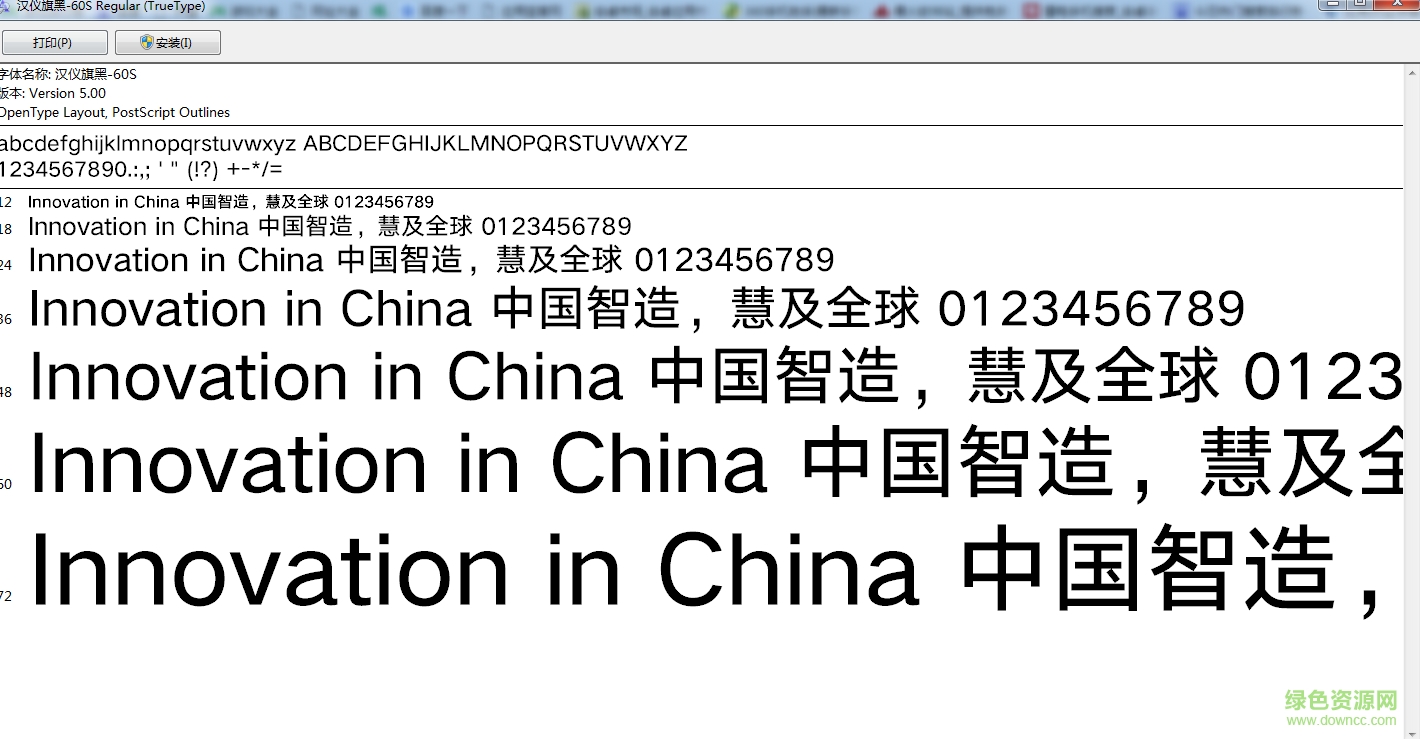
hyqihei fzs又叫漢儀旗黑60S字體,是一款有格調(diào)的漢儀字體,字體設(shè)計精致,排版效果極佳,可應(yīng)用于企業(yè)logo、品牌包裝、電視雜志、廣告設(shè)計等眾多商業(yè)領(lǐng)域!
hyqihei可謂黑體系列字體的巔峰大作,陰陽線的筆畫處理,筆觸彈性有力,字形俊秀挺拔,國際化的字體包裝方式,系統(tǒng)的中西文混搭、史上最大家族系統(tǒng),可以更完美的實現(xiàn)各類終端環(huán)境的呈現(xiàn)。